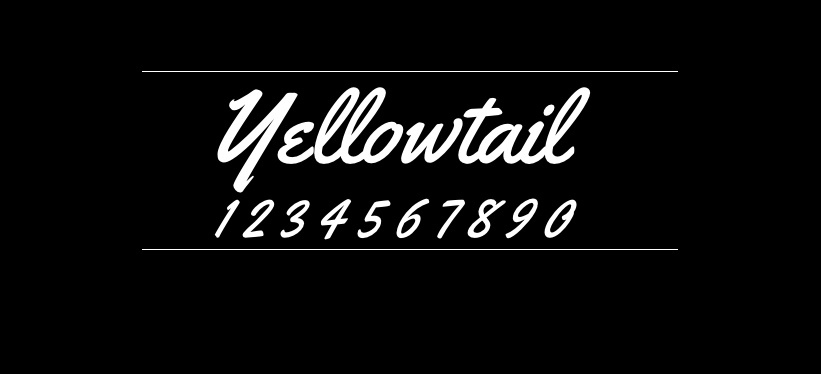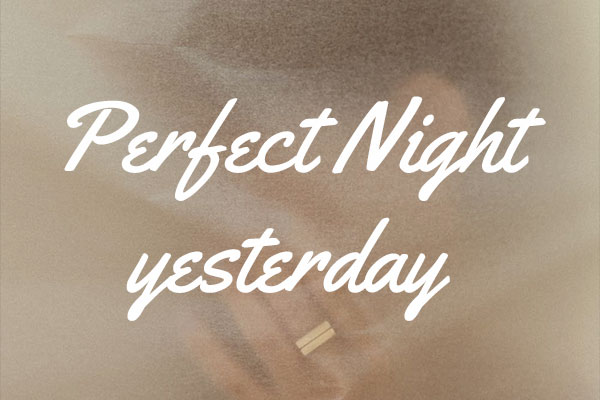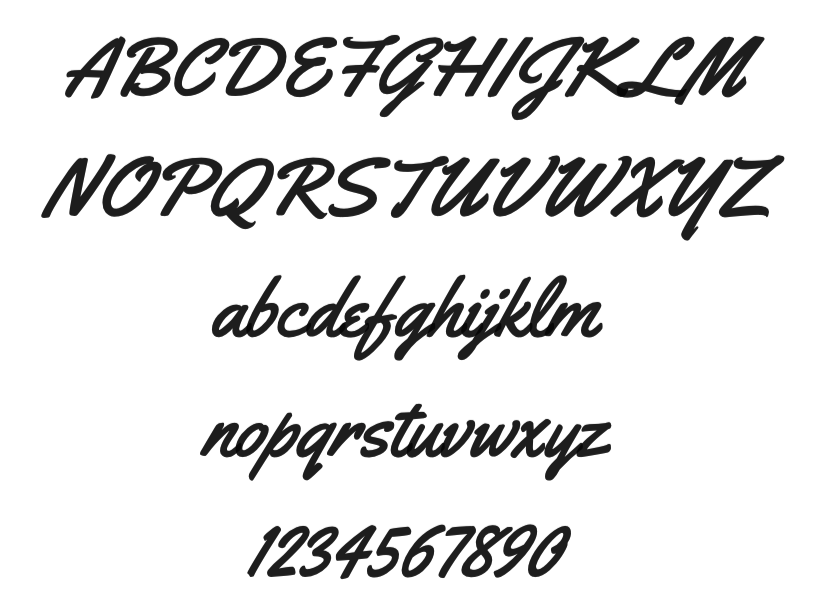
Yellowtail
Yellowtail是Astigmatic创作的一款字体,该字体使用粗笔手写风格,流畅连贯,看起来非常舒服。如果你在找一款英文手写笔迹字体,就赶紧试试这款吧!
Yellowtail是一种中等重量的老派风味平笔字体。它结合了连接形式和非连接形式,从而具有独特的外观和可读性。tail鱼向1930年的经典字体(例如Gillies Gothic和Kaufmann)致意,但其标志画家手稿的视觉节奏较为宽松。